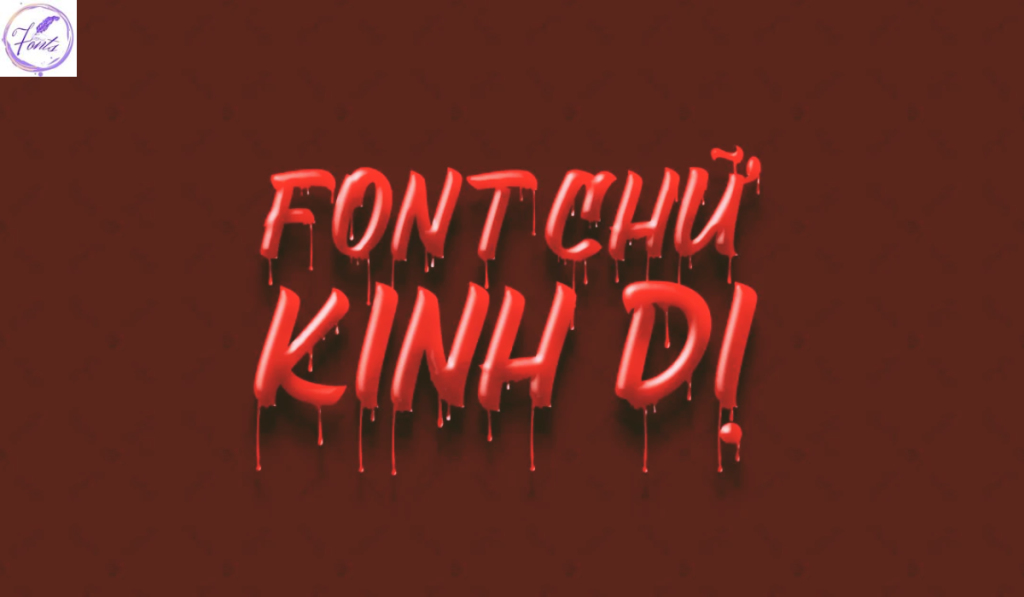
Top 10 font chữ kinh dị việt hóa Halloween ma mị
Nếu bạn đang tìm kiếm một font chữ độc đáo và ấn tượng cho dự án kinh dị của mình, font chữ kinh dị việt hóa chính là lựa chọn hoàn hảo. Với thiết kế ma mị, đáng sợ nhưng không kém phần nghệ thuật, font này mang đến không khí rùng rợn và bí ẩn cho mọi văn bản. Font kinh dị Việt hóa thích hợp sử dụng trong các dự án như poster phim kinh dị, thiệp mời Halloween, hay thậm chí là decor cho các bữa tiệc theo chủ đề kinh dị. Hãy thử sức sáng tạo của bạn với font kinh dị việt hóa và tạo nên những tác phẩm ấn tượng nhất.
Top 10 font chữ kinh dị việt hóa Halloween ma mị 2024
Font kinh dị việt hóa – Font Harry’s Brush
Font Harry’s Brush là một kiểu chữ kinh dị độc đáo, được thiết kế với độ chi tiết cao, mang đến sức mạnh và năng lượng trong từng nét vẽ. Ra mắt vào ngày 25 tháng 10 năm 2013, font này rất phù hợp cho các thiết kế áo phông, áp phích và video liên quan đến chủ đề kinh dị.
Font Exorcist kinh dị việt hóa
Font Exorcist là một phông chữ kinh dị nổi bật, lấy cảm hứng từ bộ phim nổi tiếng cùng tên. Với thiết kế độc đáo và u ám, font này không chỉ bao gồm bảng chữ cái Latinh và dấu câu mà còn mang lại trải nghiệm sáng tạo đầy ma quái. Đây là lựa chọn hoàn hảo cho các dự án liên quan đến Halloween và không gian kinh dị.
Font chữ kinh dị có chân Halloween – Font the Dark
Font chữ “The Dark” là một lựa chọn hoàn hảo cho các dự án Halloween với thiết kế kinh dị, mang đến cảm giác bí ẩn và ma quái. Font này có các ký tự sắc nét và uốn lượn, rất thích hợp cho các bức thư mời hay trang trí lễ hội.
Font chữ kinh dị chảy máu – Font the Blood
Font chữ kinh dị “The Blood” mang đến một thiết kế độc đáo, mô phỏng hình ảnh chữ viết bằng máu thật, tạo cảm giác rùng rợn và ám ảnh. Phù hợp cho các dự án liên quan đến Halloween hoặc thể loại kinh dị, font này được Việt hóa từ vector của nhà thiết kế ERburenu.
Font chữ kinh dị viết tay – Font SVN Have Heart
Font chữ SVN Have Heart là một kiểu chữ viết tay độc đáo, mang đậm phong cách kinh dị và bí ẩn. Được thiết kế với hai phiên bản, font này thường được sử dụng trong các dự án liên quan đến thể loại kinh dị như phim, truyện tranh và sự kiện Halloween. SVN Have Heart tạo cảm giác rùng rợn, phù hợp cho những ai muốn tạo nên không khí ma quái trong thiết kế của mình.
Font chữ kinh dị poster Halloween – Font SVN Bougher
Font SVN Bougher là một trong những font chữ kinh dị nổi bật, được thiết kế đặc biệt để tạo ra không khí rùng rợn cho các dự án liên quan đến Halloween. Với các đường nét sắc sảo và kiểu dáng độc đáo, font này mang lại cảm giác bí ẩn, phù hợp cho poster, banner và các sản phẩm truyền thông khác. Font Bougher đã được Việt hóa và trở thành lựa chọn ưa thích cho những ai muốn tạo điểm nhấn ma quái cho thiết kế của mình.
Font Covenant
Font Covenant là một loại font chữ được thiết kế với mục đích hỗ trợ các dự án mã nguồn mở. Font này được phát hành lần đầu vào năm 2014 và đã trở thành một phần quan trọng trong nhiều cộng đồng lập trình. Với các đặc điểm như dễ đọc và tính thẩm mỹ cao, Font Covenant giúp nâng cao trải nghiệm người dùng khi làm việc với mã nguồn.
Font chữ chảy máu kinh dị trên tấm kim loại – Horror Font
Font chữ chảy máu kinh dị trên tấm kim loại mang đến hiệu ứng rùng rợn, như những vết máu loang lổ trên bề mặt lạnh lẽo. Thiết kế độc đáo này không chỉ tạo cảm giác ám ảnh mà còn phù hợp cho các dự án liên quan đến Halloween. Font này được phát hành gần đây vào năm 2023, tạo nên không khí ma quái cho mọi thiết kế.
Font Việt hóa Bentosa
Font Việt hóa Bentosa là một font chữ độc đáo, được thiết kế để hỗ trợ người dùng viết tiếng Việt một cách dễ dàng. Font này có đầy đủ các ký tự và dấu, giúp nâng cao trải nghiệm người dùng trong việc tạo nội dung. Ngày phát hành của font là 28/07/2024, và được việt hóa bởi Kiên 2K7.
Font chữ kinh dị việt hóa script – Font Are You Serious